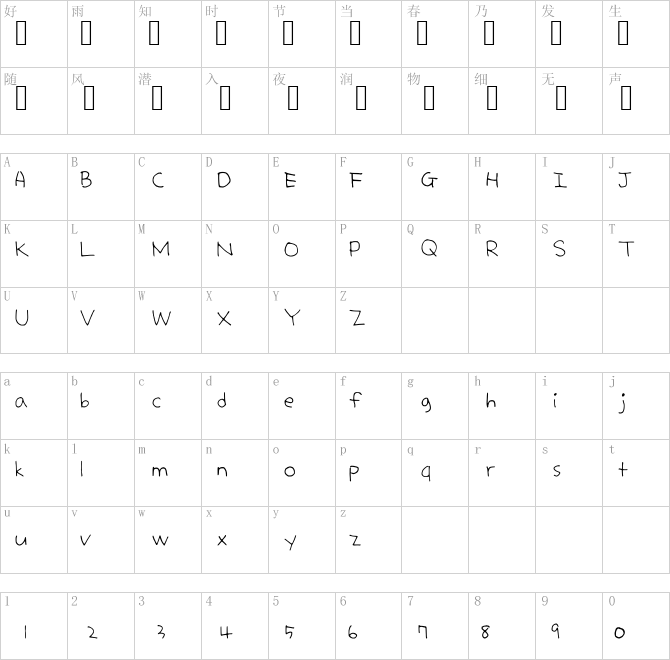
나눔손글씨 빵구니맘 손글씨韩国字体
나눔손글씨 빵구니맘 손글씨韩国字体,这款字体结构工整、笔画清晰,兼顾美观与易读性,适用于标题、正文、海报、包装、LOGO 等多种场景。字形优雅稳定,风格百搭耐看,适配日常排版与创意设计,让文字呈现更舒适、更具质感。나눔손글씨 빵구니맘 손글씨韩国字体一笔一画,皆是细节,以均衡的比例、流畅的线条打造舒适视觉体验,字形端正大气,风格简约现代。无论是商业设计、品牌宣传还是日常排版,都能轻松驾驭,让文字更有格调与力量。나눔손글씨 빵구니맘 손글씨韩国字体字体下载。
• 字体名称:나눔손글씨 빵구니맘 손글씨
• 字体风格:Regular
• 字体标识:CLOVA OCR : Nanum BbangGuNiMamSonGeurSsi
• 字体全称:나눔손글씨 빵구니맘 손글씨
• PostScript:NanumBbangGuNiMamSonGeurSsi